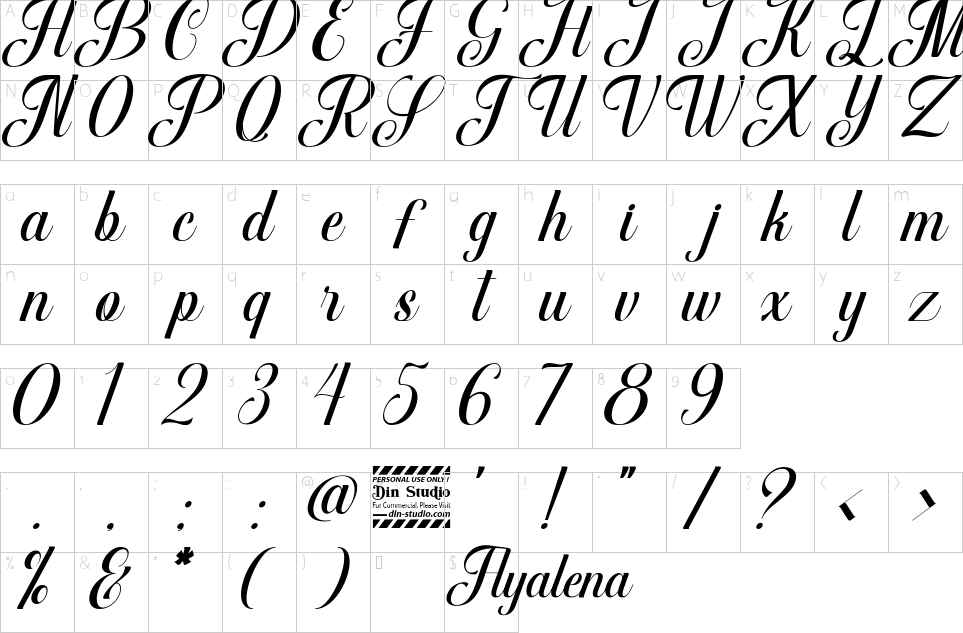
Ayalena é uma fonte moderna e elegante projetada por Donis Miftahudin, disponível gratuitamente tanto para Windows quanto para Mac. Seu design arredondado e suas linhas leves criam um equilíbrio perfeito entre personalidade e simplicidade. Os detalhes sutis e a harmonia entre os diferentes pesos da fonte a tornam uma escolha ótima para uso em materiais digitais como sites, aplicativos e editoriais de revistas. Com um visual moderno que se adapta perfeitamente a diversas aplicações, Ayalena é uma excelente opção para quem busca uma fonte de alta qualidade sem precisar gastar dinheiro. Recomendada para designers e profissionais de design gráfico, Ayalena é uma fonte versátil que certamente vai agradar qualquer usuário que busque uma fonte de qualidade para seus projetos digitais.